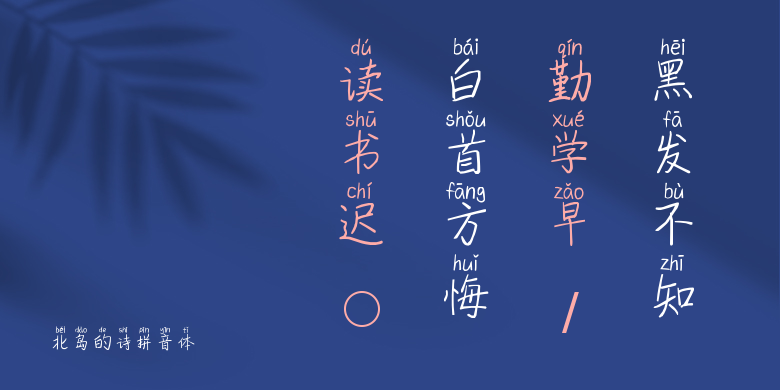
北岛的诗拼音体
北岛的诗拼音体,这款字体结构工整、笔画清晰,兼顾美观与易读性,适用于标题、正文、海报、包装、LOGO 等多种场景。字形优雅稳定,风格百搭耐看,适配日常排版与创意设计,让文字呈现更舒适、更具质感。北岛的诗拼音体一笔一画,皆是细节,以均衡的比例、流畅的线条打造舒适视觉体验,字形端正大气,风格简约现代。无论是商业设计、品牌宣传还是日常排版,都能轻松驾驭,让文字更有格调与力量。北岛的诗拼音体字体下载。